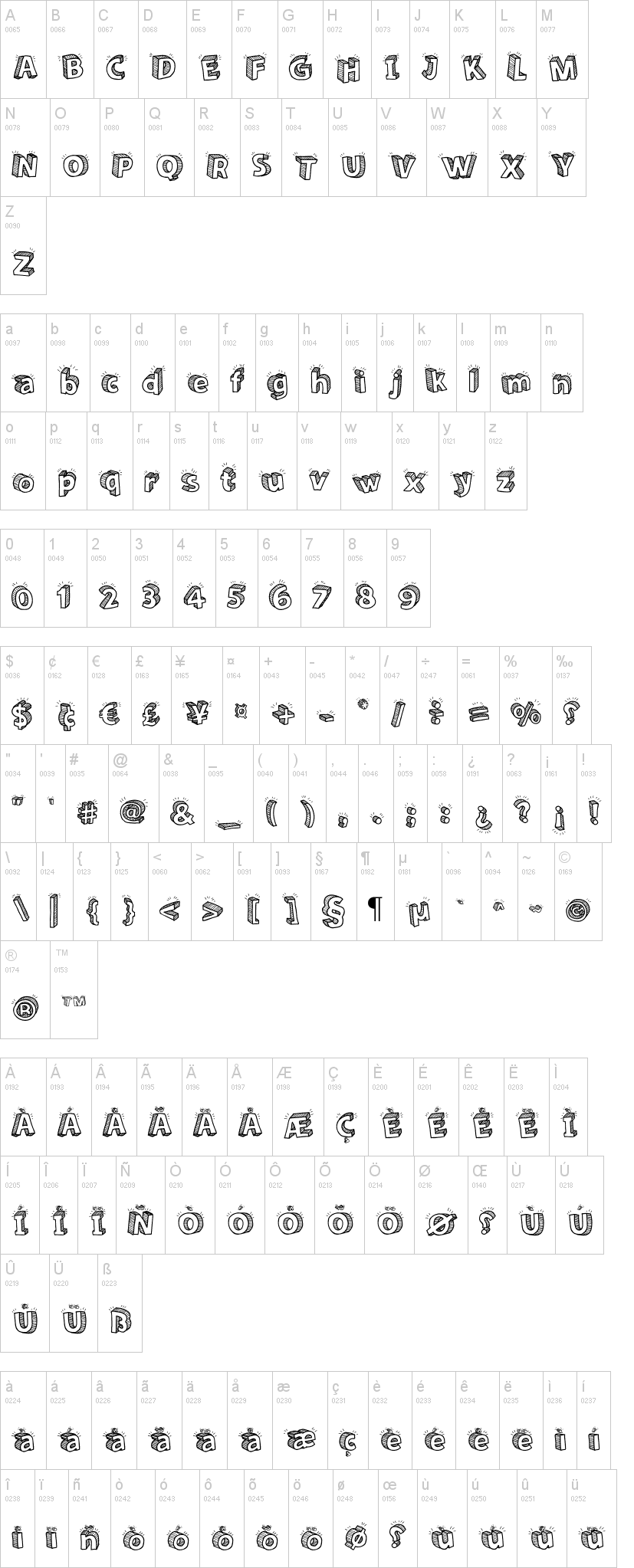
Sketch 3D
? Sketch 3D 字体是一种独特的三维字体,它可以创建立体字体,具有深度和立体感,同时可以调整字体的大小,颜色,阴影,纹理等。它可以用于创建复杂的三维标志,广告,展示,游戏,动画,电影等。它可以使您的文字和标志看起来更有立体感,更有表现力,同时又能够以更低的成本实现更高的视觉效果。
Sketch 3D是一款非常不错的手写艺术字体,具有很好的视觉感,适合于文化类的宣传设计、商业类品牌的广告和产品包装设计以及个性化文字排版等较多场景。
Sketch 3D字符映射图